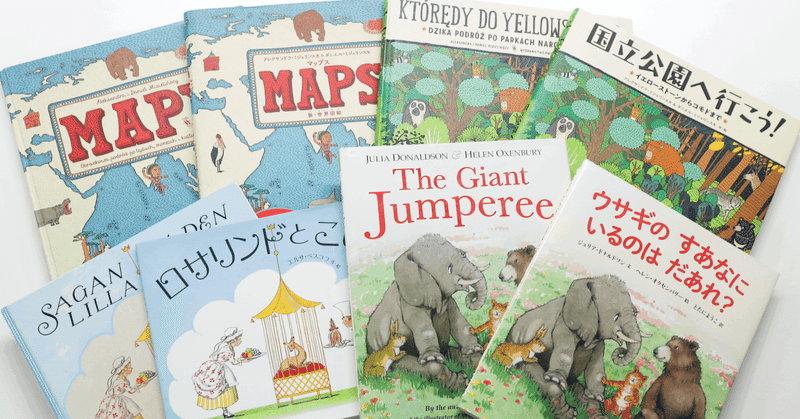
原作と翻訳絵本を比べたら書体がローカライズされていた話
書体を意識して見るのは慣れていないと難しい。特に普段使わない言語ならなおのこと。みなさんは欧文書体を意識して見たことはありますか?
店の看板、メニュー、電光掲示板、雑誌……和文書体のすぐそばに欧文書体はいます。
もしかして欧文書体にフォーカスしたら書体にまつわる面白いことが見つかるのではないか……?そんな思いつきがこの記事のきっかけになりました。
日本語に翻訳されると書体も変化する不思議
欧文書体を意識するには、まずは見慣れた和文書体と比較するときっとわかりやすいはず。そう思って翻訳絵本に目をつけました。
翻訳絵本とは、オリジナルが海外にある絵本を日本語に翻訳して出版された書籍のことです。
調査すると嬉しいことに書体にまつわる面白い発見がありました。
海外の絵本の本文ではセリフ体(Serif)が多く使われ、日本語版では様々な書体に変化することがわかりました。セリフ体は和文書体でいう明朝体のことですが、なぜそのまま同じ系統の書体が選ばれなかったのでしょうか。
海外と同じ書体の雰囲気に合わせていないことがとても不思議でした。
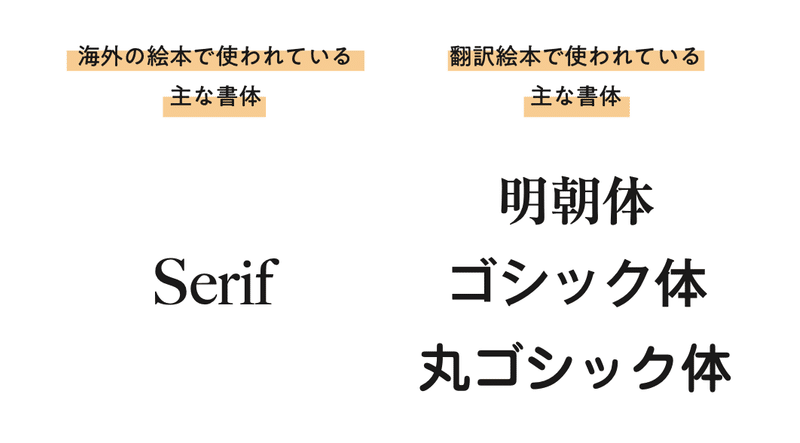
翻訳絵本はさまざまな書体で文字が組まれていました。
これはきっと何か理由があるのかもしれない。
現場の声を聞くべく、実際に翻訳絵本を編集している徳間書店さんとデザイナーさんにインタビューしました。
たくさん絵本を紹介していただきながら、書体の選び方や実際に海外の作者とのやり取りの中で受けた文字に関わるカルチャーショックについて、たっぷり伺いました。
翻訳絵本ならではの書体の選び方
ー まず翻訳絵本の制作フローを教えていただけますか?
田代 原作が海外の絵本は、日本語訳→組版→入稿→修正→校了というフローで制作します。
組版は訳がある程度かたまってからフォントを選定し、絵と合わせます。だいたい校了直前まで文章に手を入れることが多いです。
ー フォント選びは田代さんのような編集者さんが担当しているのですか?
田代 徳間書店では、基本的には編集者が絵本の本文を組むので、自分で本文用のフォントを選びます。私の場合大体使うフォントは決まっています。明朝はリュウミン、ゴシックだと中ゴシックBBB、ゴシックMB101、新ゴあたりから選んでいます。
中にはフォントが好きな編集者もいて、よくモリサワのフォントラインナップと睨めっこしてますよ。
ただ絵本は、近年、国際共同印刷(コプロダクション)といって、海外で印刷製本することも増えています。その場合はデザイナーさんに本文データを作ってもらうため、フォント選びも一緒に行うことが多いです。
ー ではこちらの絵本は?
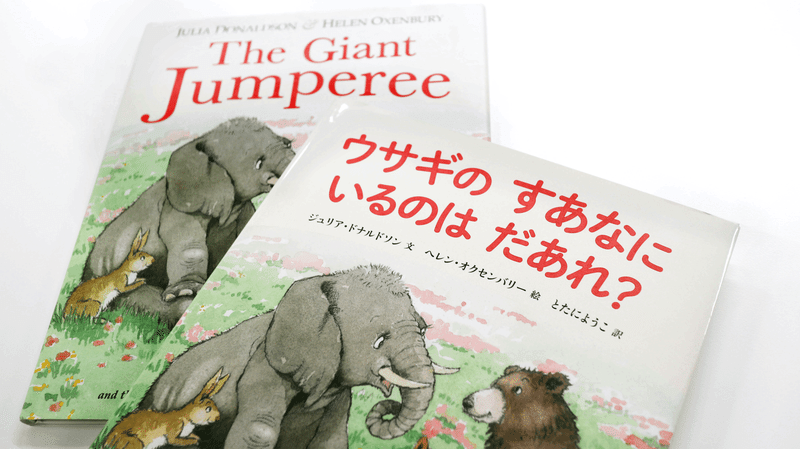
田代 『ウサギのすあなにいるのはだあれ?』は海外で印刷と製本をしています。なので中も全部デザイナーさんに組んでもらっています。
書体は原作の世界観と登場人物の声で決まる
ー この絵本は原作と日本語訳の書体の使われ方が異なりますよね。明朝体にあたるセリフ体が原作に使われているのに、日本語版では丸ゴシック体が使われています。この書体選びの背景や理由はありますか?
田代 担当してくださったデザイナーさんに聞いたところ、初めは明朝体2種類と丸ゴシック体1種類で見本を組んだそうです。この絵本はユーモアのあるお話ですが、絵はそんなにコミカルな雰囲気ではありません。そのため明朝体で組んでしまうと、絵本そのものがシリアスな印象になり過ぎてしまうため、最終的に丸ゴシック(丸ツデイ)に決まったと聞きました。
書体の選び方として、日本語の場合は最初に明朝体とゴシック体どちらをメインにするか決めます。その判断材料がストーリーとイラストです。
例えばこの絵本は明るい話だから、緊張感を与えないゴシック体や丸ゴシック体にしよう、とか......。一方で同じ明るい話だけど、絵のタッチが繊細で明朝体とマッチするから、明朝体にしようと考えたり…...。この方向性が決まった段階でフォントを選びます。
原作がセリフ体だったからといって明朝体を選ぶのがセオリーというわけではなく、その作品の世界観を大切にしながら書体を選んでいます。
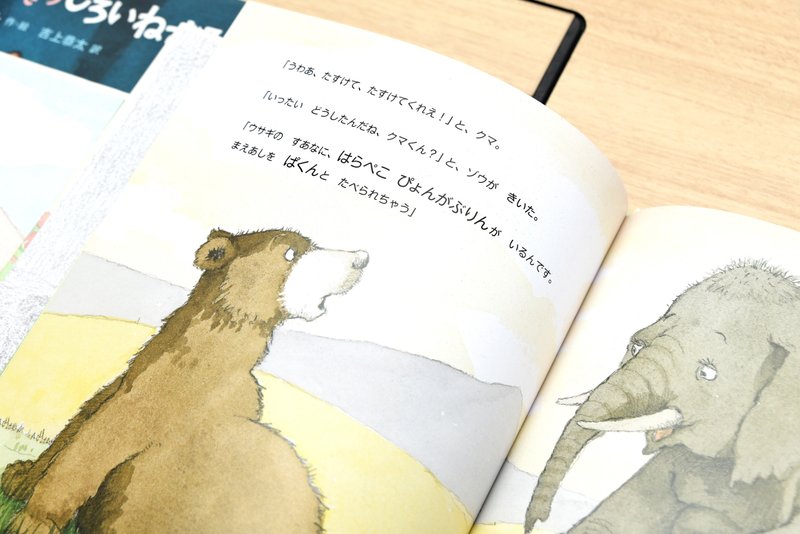
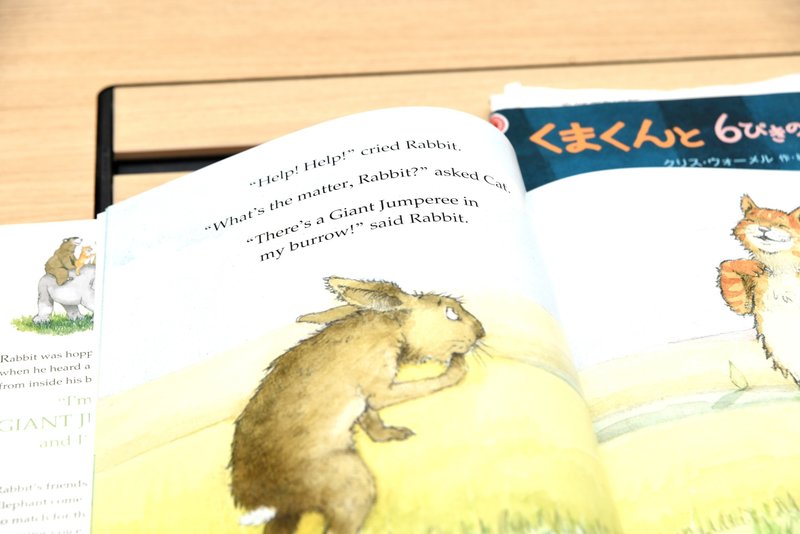
ー 田代さん自身が携わった絵本について、どのような書体選びをしたのか教えていただけますか?
田代 私が編集した絵本で紹介したいのはスウェーデンで1924年に出版された絵本『ロサリンドとこじか』です。徳間書店では、日本語版を2021年に出版しました。
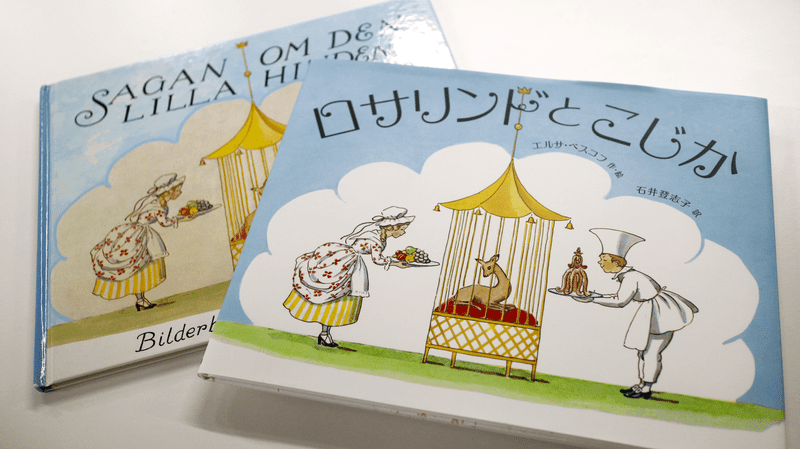
田代 この絵本は物語が入れ子構造になっていて、冒頭がおじいちゃんと女の子の会話、本編が2人の作ったお話になっています。これも本文にセリフ体が使われているのですが、全てイタリック※になっています。
※イタリックを使う場面
強調、 CDアルバムタイトル(曲名はローマン体で引用符で囲う)、美術などの作品名、映画タイトル、書籍名、雑誌名、新聞名、外国語、小説などの過去の回想シーンや手紙の内容などの表記
ー ほんとに全部イタリックですね!
田代 イタリックはどうしようかなあ.…..とちょっと悩みました。もともとイタリックというのは日本語にはない手法です。技術的には可能ですが、子どもの本で斜体を使うのはふさわしくないと考え、ひとまずお話がクラシックなことから本編はリュウミンにしようと決めました。
そして、入れ子になっている物語の冒頭部分、おじいちゃんと女の子の会話のシーンは、本編と違うフォントにしてストーリーがちがうことを伝えたいと思い、教科書体にしました。ゴシック体も検討したのですが、優雅な雰囲気のこの本がいきなりゴシック体で始まるのはしっくりこなくて。また、この絵本の中にある王様のおふれに使ったフォントとも重ならない書体にしました。
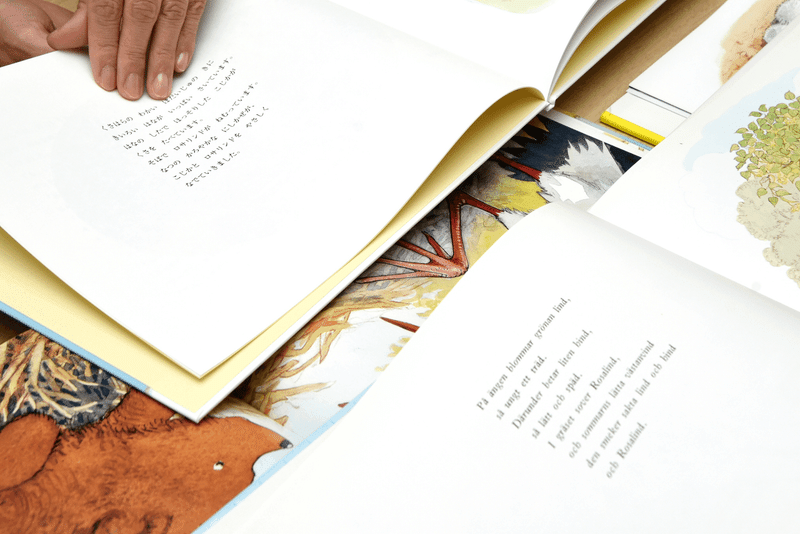
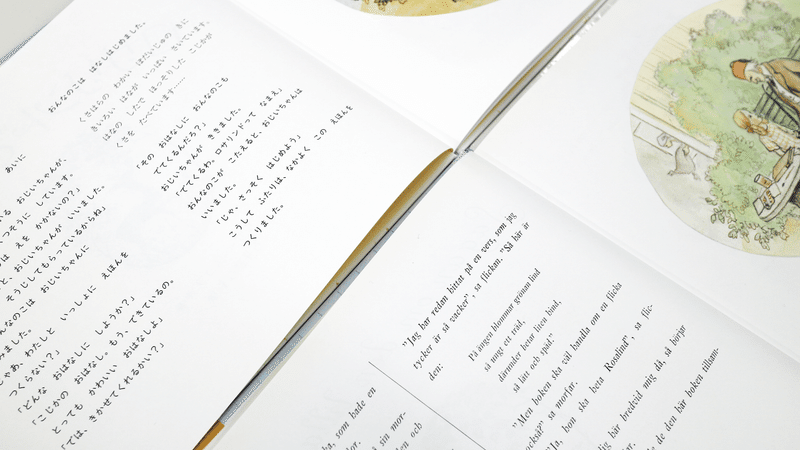
ー 明朝体は本編、教科書体は女の子とおじいちゃんの会話、ゴシック体は王さまのおふれ。書体選びは物語が変わるタイミングや登場人物の声を意識しているということですね。とても興味深いです。
海外の作者とのやり取りで気づいた書体にまつわるカルチャーショック
田代 これまでの話は普段の編集事情の話でしたが、ちょっとイレギュラーなケースもありまして。百足屋さんにも全面的に協力いただいたこちらの絵本、『マップス』と『国立公園へ行こう!』です。
百足屋 作者はポーランド人の夫婦、アレクサンドラ・ミジェリンスカさんとダニエル・ミジェリンスキさんで、お二人は一緒に書籍制作をしています。特に、夫のダニエルさんが日本の漫画やアニメや映画が好きで、その影響を受けて絵本を作っています。私はこれまでに6冊携わりました。
ー この2冊は普段の編集作業とどんなところが違ったのでしょうか?
田代 この作品も国際共同印刷で、ポーランドでまとめて印刷されました。1か所でいくつかの言語の版を一緒に印刷をするので、単独で印刷するよりも、部数がトータルで大きくなり、単価が抑えられるロジックです。共同で印刷するために〆切には遅れることができないのでプレッシャーを感じました。
さらにもう1つ他の作品と異なる点は、各国の翻訳版の組版データを作者自身が全て管理していたことです。
百足屋 ミジェリンスキ夫妻はタイプデザイナーでもあるので、文字にこだわりがあったからという背景もありますね。
田代 そうなんです。特に『マップス』は30言語以上に訳され、全ての言語について作者が組版のチェックをしています。まずフォントの選定、そして全ページ組んだら組版の仕上がりをチェック。
日本語版の場合はアルファベットの文字ではないので、フォント選びから行い、監修を受けるのです。
ー フォントにも作者のチェックが入るというわけですね!
百足屋 そういうことです。2冊とも原作に使われている欧文フォントは作者が作字した手書き風のデザインでした。例えば同じフォントでも、「A」という文字を何種類か作っていて、違うデザインの「A」がたぶんランダムに出るようになっています。
『マップス(原作)』より。
ー 『国立公園へ行こう!』ではどんなことが大変でしたか?
田代 書体選びという話からは外れてしまうかもしれませんが、日本語の組版をどうやって理解してもらうかが大変でした。
この作品は多くのページがコマわりになっていて、長めの説明もすでに固定されたテキストボックスの中に入っていました。
でも、翻訳すると、原文と同じ長さになるとはかぎらないんです。ときには、空白ができてしまうこともあるのですが、作者たちは、テキストボックスの最後に空いた行ができてしまうことをとても気にしていて、「たくさん改行していいから、ボックスの下まで埋めて」と言われました。
日本語の組版では長文は「1行何文字」と決めて、ボックス型に組むことが多いですよね。でも、この本では文節で改行することとし、早めの改行で行を増やすことでなんとか空いた行を作らないようにしました。
田代 それでも作者に枠の空白について指摘を受け、文章を変えることも一時は検討しました。
ただよく考えると、作者が気にしているのは “枠の余白”。つまり見た目の話です。この書籍を誰が読むのかを考えたとき、デザインで文字を見ている人ではなく日本語話者だと気づき、最終的に日本人に読みやすい文字組みを優先したいことを伝え、了承いただきました。
デザインとして見ることより、言語を理解して読むことの方が大切だということをはっきり伝えなければならないという気持ちでした。
百足屋 本当にここは頑張りましょうという気持ちで田代さんも伝えていましたよね。
デザインする側からの感想としては、原作のテキストボックスの枠は動かせないこともあり、制限のある中で、日本語組版として違和感が出ないようにすることに、本当に苦労しました。
なによりも言葉を実際に読む人を意識した組版ルールに則ることが重要だと私も思います。日本語と外国語では文字数も違えば、ふりがなの有無もあります。全く同じような見た目にすることはできなくて当然だと思います。
ー では『マップス』の編集作業はどんなことに苦労しました?
田代 こちらも色々大変でしたね。そう思うのはこの作品がダニエルさんと初めてやりとりした絵本だったからかもしれません。
なかでも苦労したのは、見出しとキャプションのフォント選びです。
原作の見出しには作者が手がけた手書き風のセリフ体、キャプションには手書き風のスクリプト体(筆記体)が使われています。
見出し用とキャプション用でそれぞれ合いそうなフォントを何種類か提案しましたが、2つのフォントの間で強弱が欲しいなどという指摘があり、決まるまでに何度もやり取りがありました。
あとがき
翻訳絵本はイラストやストーリーの雰囲気、場面転換や登場人物の声、そしてなにより誰が読む本なのかを意識した上でさまざまな書体が選ばれていることがわかりました。読み手が慣れ親しむ言語に寄り添いたいという田代さんと百足屋さんの想いに感銘を受けました。
今回は翻訳絵本で和文と欧文を比較しながら、和文書体の魅力を再発見しました。そうなると、欧文書体も知りたいですよね?